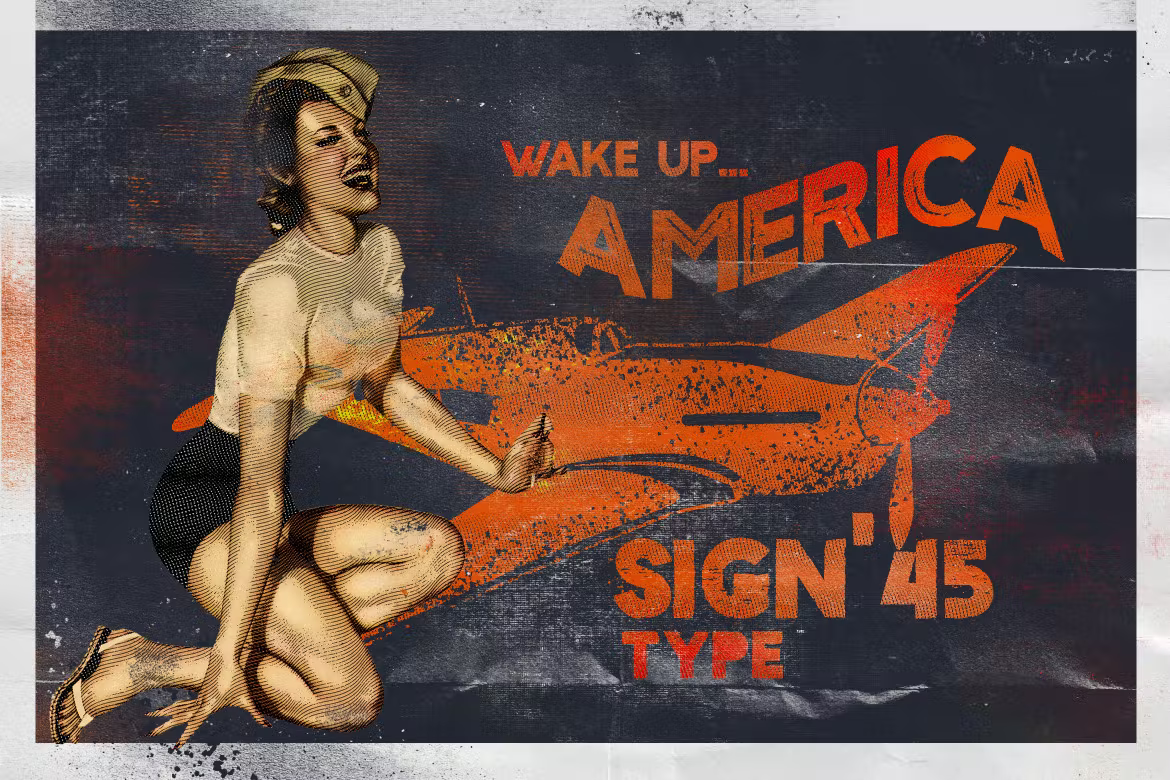
Sign 45 Typeface Font
Description de Sign 45 Typeface Font
Avec Sign ’45 Typeface, vous pouvez faciliter la transmission du message dans votre conception. Utilisez-le pour un affichage, un étiquetage, des vêtements, une scène de film, une affiche, un titre de film, des concerts, des couvertures d’album, des logos et bien plus encore.
La police dispose de 6 styles et est idéale pour les projets rétro et vintage, des designs clairs aux designs bruts.